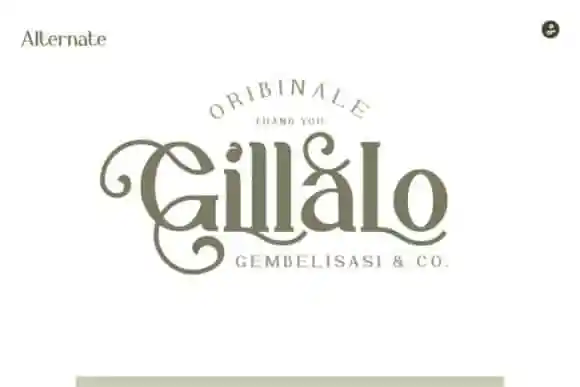
Gillalo Serif Font
A Gillalo Serif Font é uma elegante escolha para criar marcas de alto padrão, oferecendo uma coleção especial de ligaturas e alternativas que trazem sofisticação à sua marca. Seja no design editorial, editoriais digitais ou até mesmo em materiais gráficos impressos, a Gillalo Serif Font proporciona um toque de classe às suas criações. Esta fonte é ideal para quem busca transmitir uma imagem sólida e estabelecida, com estilo e sofisticação. Combinada com seu design curvilíneo harmonioso, a Gillalo Serif Font se destaca em qualquer aplicação visual, tornando-a um investimento valioso para designers profissionais e amadores que buscam um grampo excepcional para suas mensagens.